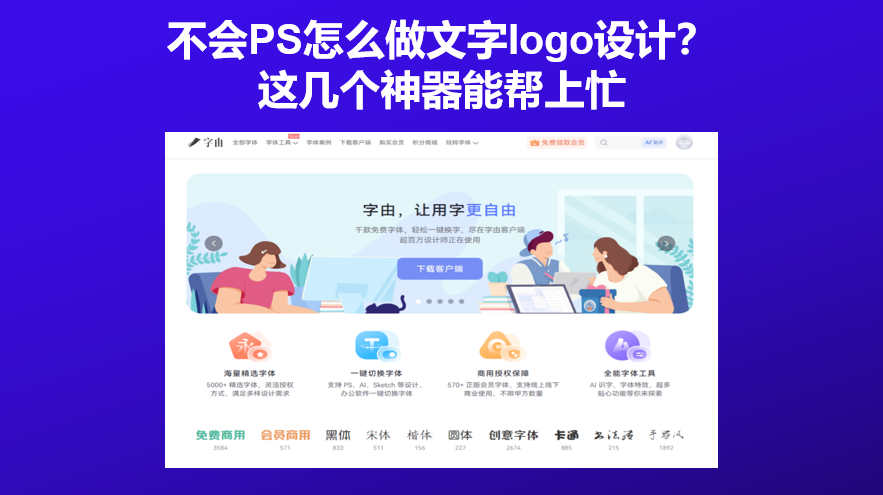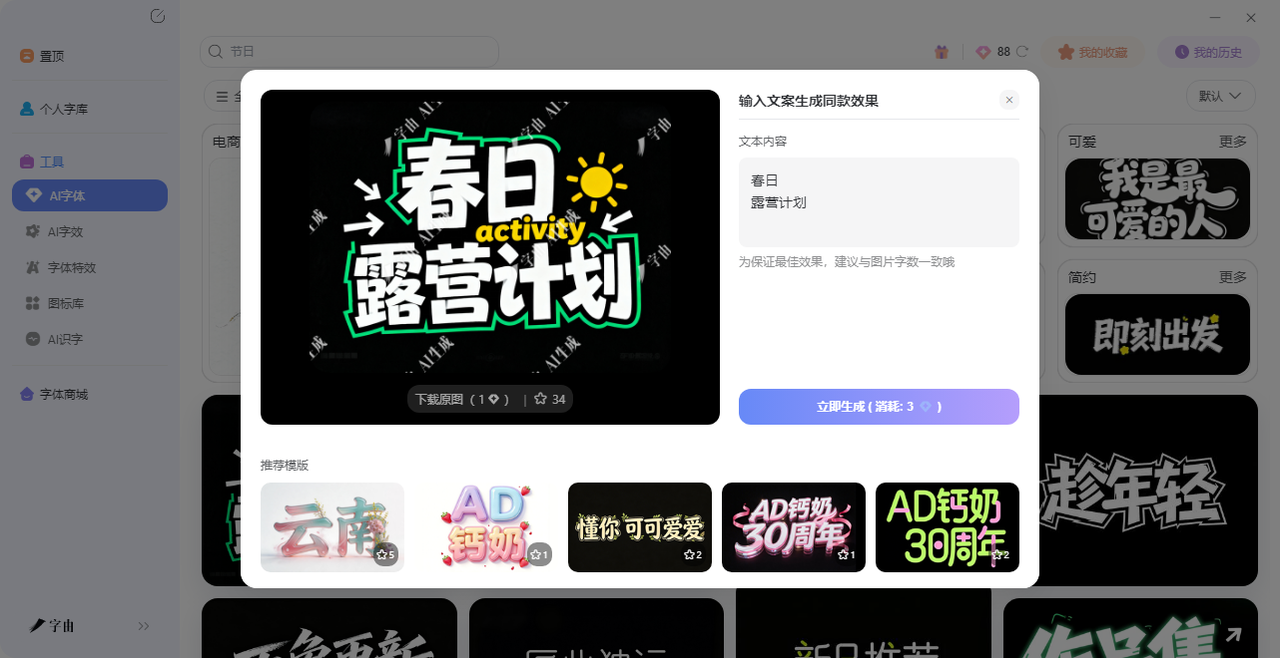
不会PS怎么做文字logo设计?这几个神器能帮上忙
如果说你是刚入门的设计师,想设计出一个有自己风格的LOGO,可能会比较困难,先别提个人品牌,就连训练的时候可能都困难重重。但是现在市面上有很多AI工具,能够帮助你设计LOGO,在你没有灵感或者是技能还比较生疏的时候,文字logo设计AI工具完全是能够帮上忙的,今天我就整理了 6 个好用的在线logo制作工具,看看哪个适合你。
先聊第一个,也是我自己用得最顺手的——字由(hellofont.cn)。字由是国内一个集字体发现、管理、应用于一体的综合字体平台,注册用户超过2000万,收录了上万款字体,免费商用字体超过3500款。很多人只知道字由是个字体管理工具,但它做文字型logo其实特别方便。
字由的AI字体功能,可能是目前做文字logo设计门槛最低的工具之一。操作大概只需三步就可以完成:打开字由客户端,在“工具”菜单里找到“AI字体”,浏览里面的模板库。不管是电商促销用的醒目艺术字、新媒体配图的文案字,还是小店用的文字logo,分类里都有,电商、国风、涂鸦、科技感这些风格全都能找到。
看中哪个模板,点“做同款”,输入你自己的品牌名称或logo文案,点“立即生成”,等25秒左右就能看到成品。生成后背景可以调成透明,直接下载PNG图片就能用到海报、头像、名片里了。
字由AI字体的一大优势是字体适配性强,生成的文字logo笔画规整、没有错字,不会出现字体扭曲或者间距混乱的问题,风格统一度很高。而且依托正版字体库,生成的logo文字部分可商用,能提供授权证明,用着放心。每日登录还能领免费算力,基础商用需求基本不用额外花钱.
想要简洁文字logo、注重字体规范和版权、不想折腾复杂操作的个人和小商家,比如小店招牌、自媒体头像、个人工作室logo,字由AI字体都能搞.
2、Tailor Brands
第二个网站叫Tailor Brands。这是一个专门为创业者和中小型企业打造的AI品牌设计平台,不只是做logo,还能帮你搭建一整套品牌视觉体系。Tailor Brands的AI logo生成逻辑和一般工具不太一样。你输入公司名称和行业后,它不只是问你喜欢什么颜色什么风格,还会问你的品牌性格和目标受众。它用AI算法生成多个logo方案供你选择,整个过程几分钟就能完成。
除了logo,Tailor Brands还能自动生成品牌手册,包含你的品牌配色、字体、视觉规范,确保所有营销材料的风格保持一致。它还内置了网站搭建工具、名片设计、社交媒体素材制作等功能。如果你是一个刚起步的创业者,想在同一个平台上搞定logo、名片、网站甚至商标注册,Tailor Brands绝对很适合你。
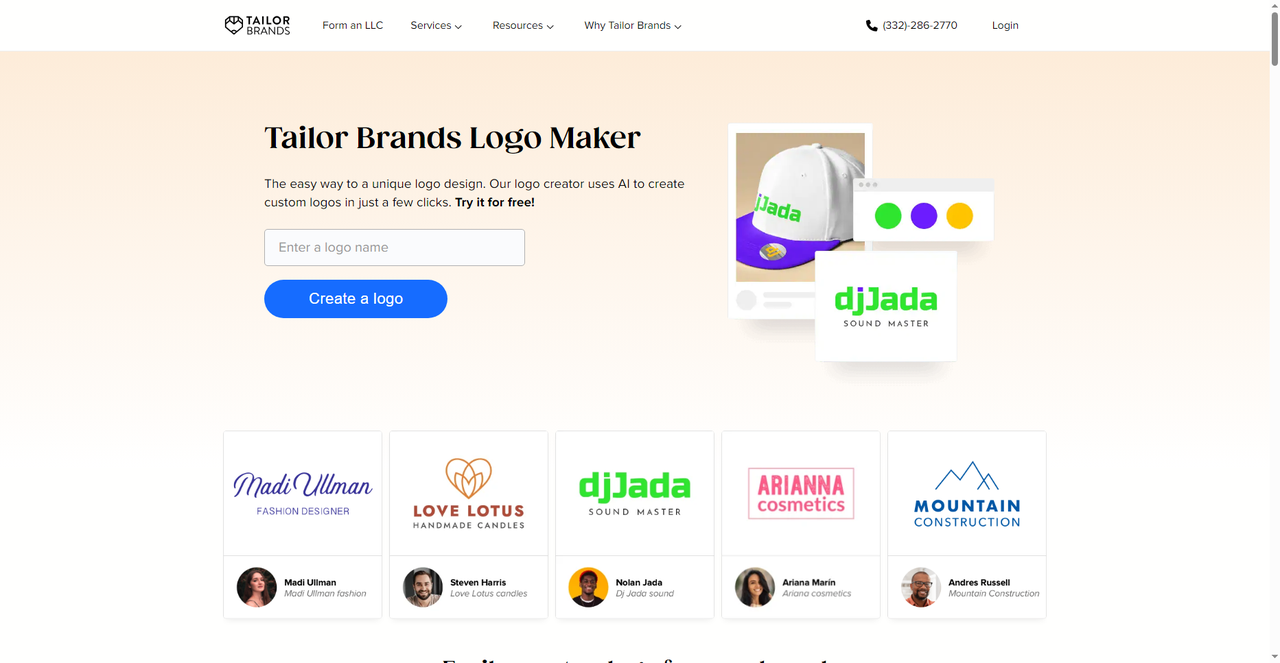
3、Looka
第三个要介绍的网站叫Looka。和Tailor Brands类似,Looka也是一个AI驱动的品牌设计平台,但在logo生成这一步做得更轻量。用Looka做文字logo设计,流程是这样的:输入公司名称,选择行业类型,再选几个你喜欢的颜色和设计风格,AI就会在几分钟内生成几十款不同风格的logo方案供你选择-。生成后可以在线调整字体、颜色、布局,直到满意为止。付费后可以下载超过15种高分辨率文件格式,包括SVG、PNG、EPS和PDF。
Looka的logo设计风格现代,很少出现那种一看就是模板堆出来的廉价感。如果你想要一个看起来比较专业、不像是自己随便做的logo,Looka可以优先试试看。它也能延伸出名片、社交媒体素材等品牌套件,对品牌统一性有要求的用户会很受用。
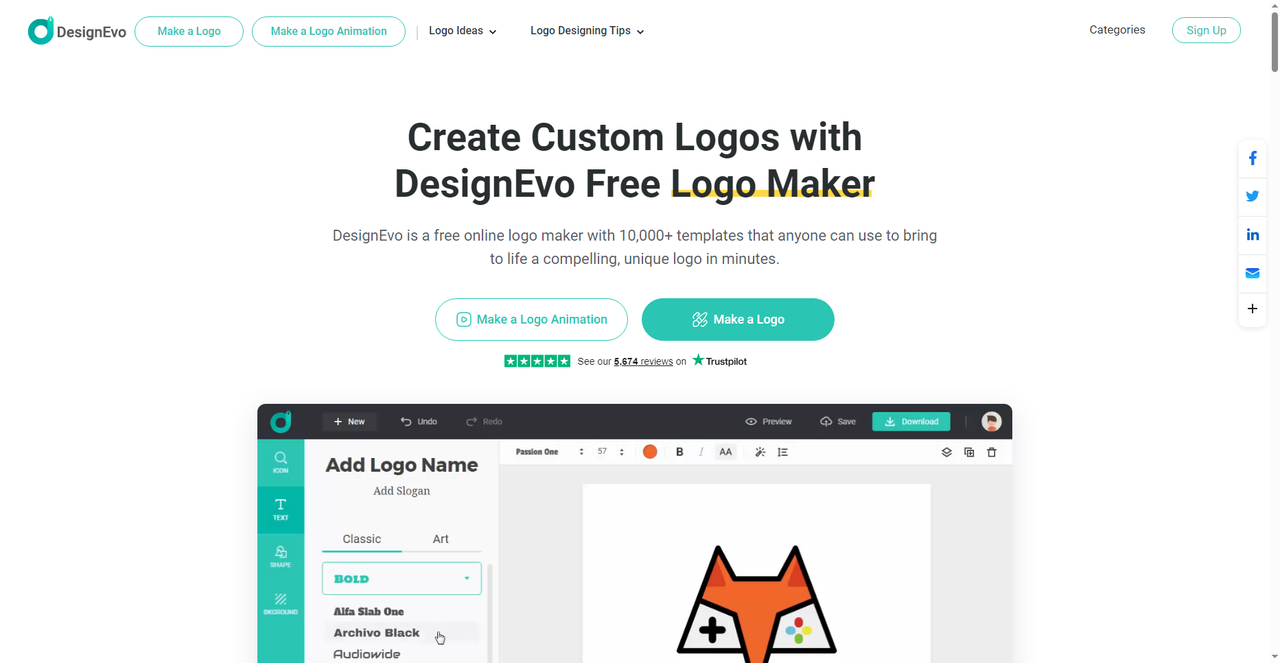
4、DesignEvo
第四个网站是DesignEvo。这是一个纯在线的logo制作工具,特点就两个字:省事。DesignEvo有超过10000个专业设计的logo模板,覆盖餐饮、科技、教育、时尚等二十多个行业。操作分三步:选一个喜欢的模板 → 修改文字和图标 → 下载导出。编辑器支持拖拽操作,你可以随意调整颜色、字体、大小和布局,不需要任何设计基础。
DesignEvo还内置了数百万个矢量图标和100多种字体,如果你不满意模板自带的图标,可以自己搜索替换。完成设计后可以预览logo在名片、网站等不同场景的显示效果,再决定要不要微调。需要注意的是,免费版下载的分辨率有限,如果需要高清PNG(5000×5000像素)或SVG矢量文件用于印刷品,需要升级付费版本。
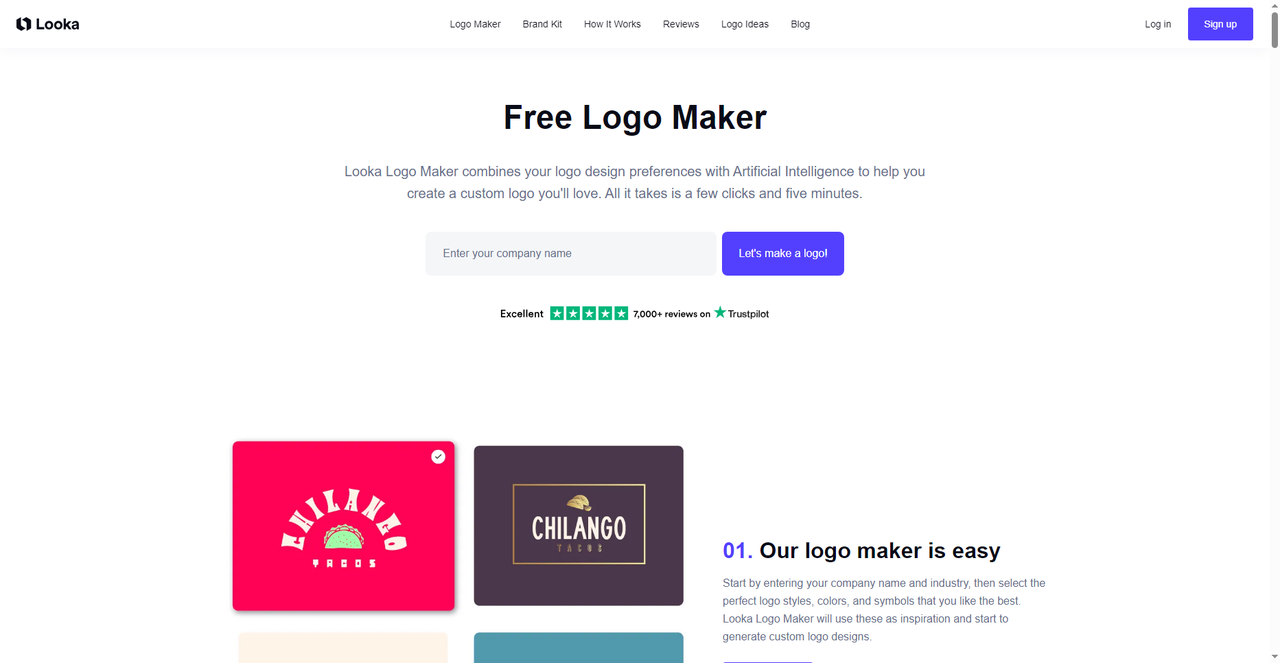
5、designcom
下一个要介绍的网站号称“世界排名第一的AI logo生成器”,并且提供,免费尝试的机会。这个网站的logo生成器输入公司名称和简短描述后,AI会在几秒内生成几十个logo方案-。它的模板库极其庞大——超过36万个logo模板和100多万个设计模板,覆盖所有行业和风格-。
和前面几个工具比,它最大的优势是平台够全。它不只是一个logo制作器,还集成了AI网站生成器、AI名片制作器、AI海报和宣传单生成器、AI演示文稿工具等超过50种设计工具-。你可以在同一个平台完成logo、网站、名片、社交媒体素材、宣传物料等一系列品牌设计,品牌一致性自然有保障。
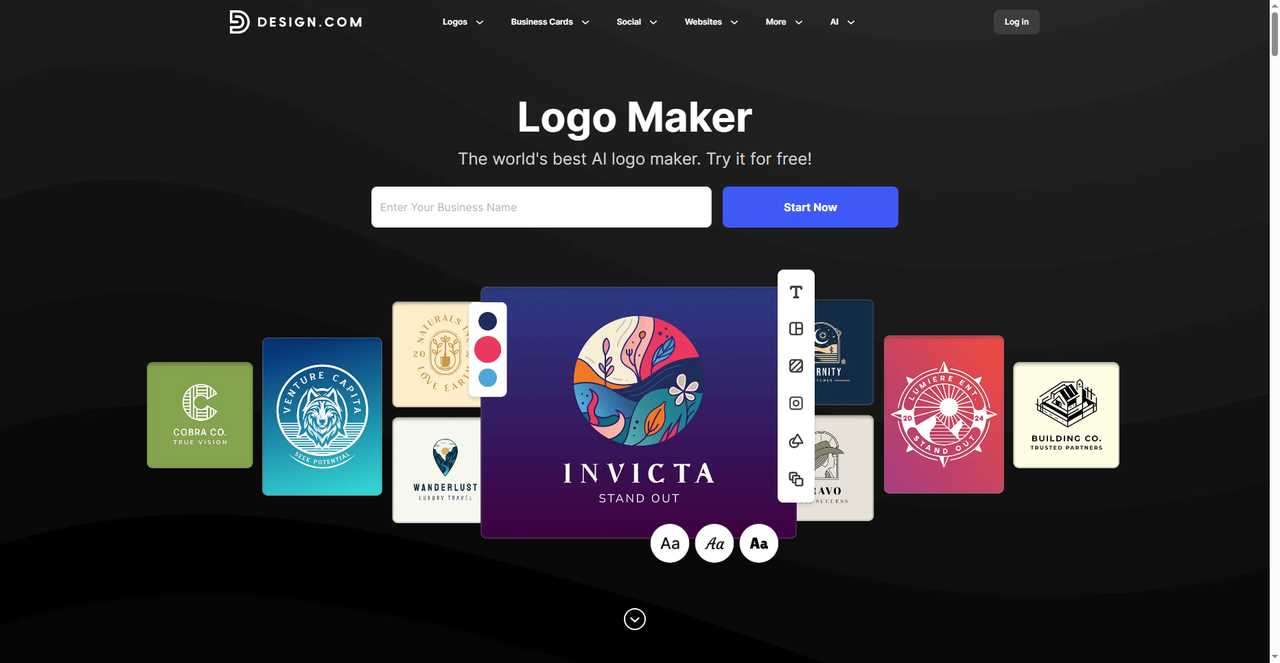
6、BrandCrowd
最后一个网站是BrandCrowd。它家最大的卖点是模板库规模和质量——拥有超过35万个logo模板和100多万个设计素材,而且每个模板都由专业设计师手工制作,不是从图库里面扒的.BrandCrowd提供了完整的品牌素材包升级选项,包括名片、社交媒体封面、信纸等,全部和你的logo风格保持统一。如果你需要的是一个高质量、有设计感、不像是模板直接套出来的logo,BrandCrowd是很好的选择。
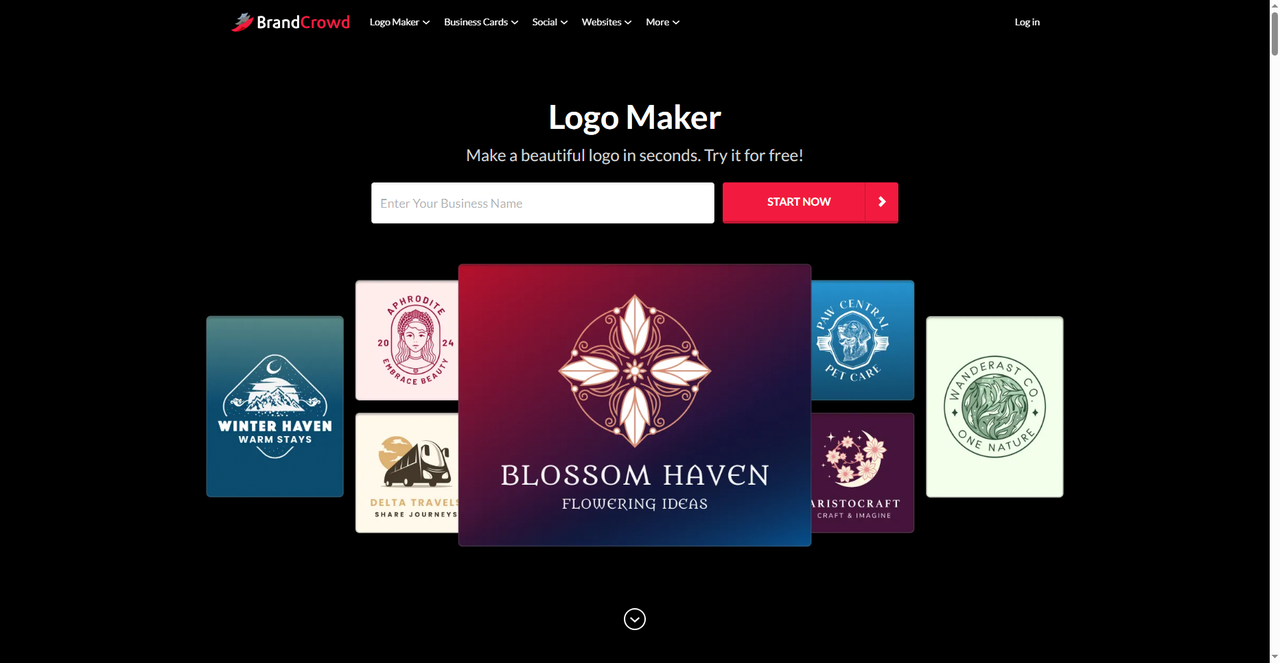
做文字logo设计这件事,现在真的不用太纠结。先想清楚自己需要什么样的logo——是纯文字型、图形+文字、还是全套品牌视觉?然后从上面挑一个工具,输入品牌名、选个模板、改改颜色字体,几分钟就能做出一个能用的logo。等以后业务做大了,再找专业设计师精修也不迟。以上就是今天介绍的工具了,如果你的logo主要是文字型,想要字体规范、版权清晰、操作简单,那字由的AI字体功能最适合,模板丰富、每天免费算力够用,文字logo设计用它完全能搞定。